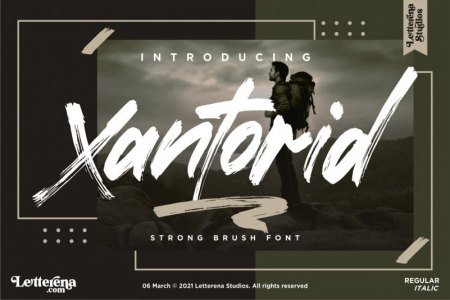
Xantorid Font
Xantorid é uma fonte de pincel premium, adequada para qualquer projeto, como: logotipos, projetos de marca, designs de utensílios domésticos, embalagens de produtos, canecas, citações, pôsteres, sacolas de compras, camisetas, capas de livros, cartões de visita, cartões de convite, cartões comemorativos, etiqueta, fotografia, marca d'água, eventos especiais e todos os seus outros projetos de luxo que precisam de um gosto forte de pincel.